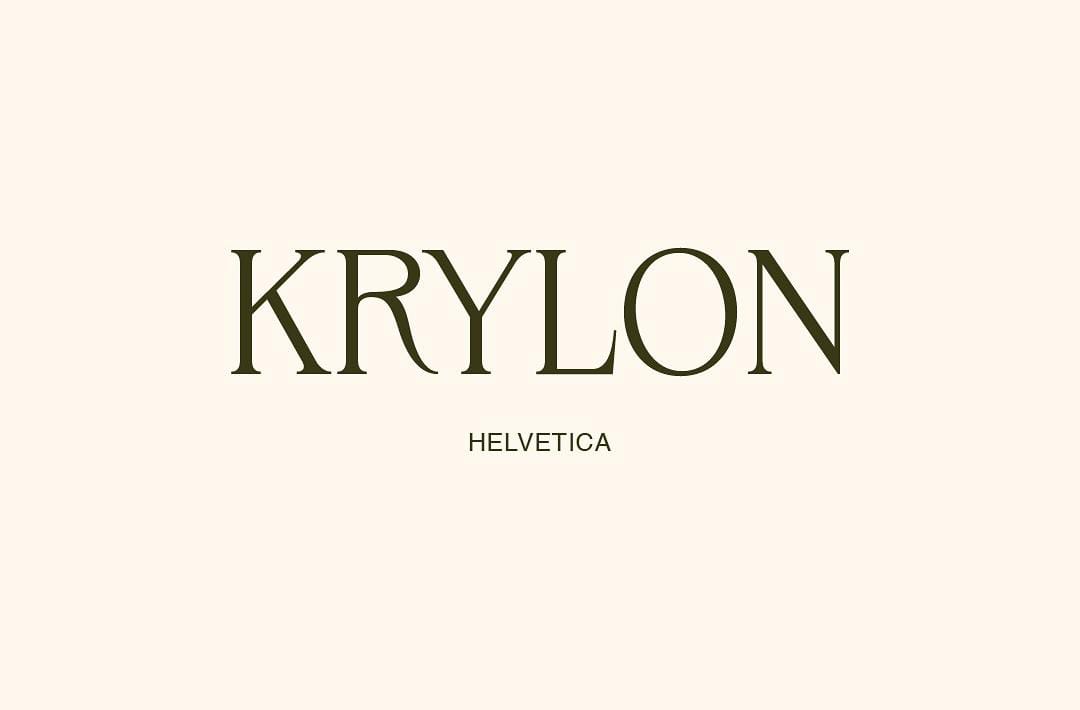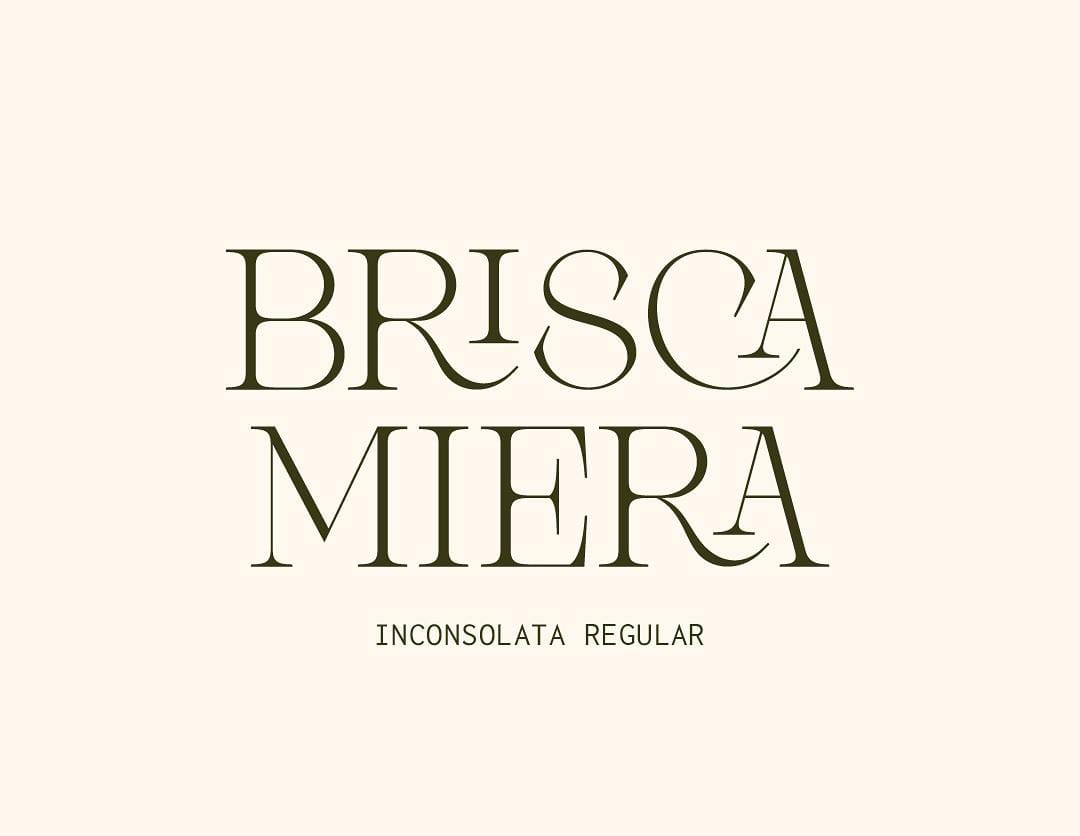
Untuk memastikan branding tampil profesional maka penting untuk memilih kombinasi elemen yang profesional. Tipografi menjadi salah satu elemen penting dalam branding sehingga harus dipilih yang relevan. Untuk kebutuhan brand kecantikan, kombinasi font harus tampil elegan, mewah dan minimalis agar relevan.
Brand kecantikan identik dengan citra yang feminim, elegan dan mewah, hal ini akan terlihat melalui penggunaan elemen-elemen yang elegan. Desain brand kecantikan yang elegan akan meningkatkan daya tarik visual dan menarik perhatian target pasar. Untuk pilihan gaya tipografi yang digunakan harus dipilih yang elegan, unik dan sesuai dengan citra brand.
STYLE LOGO KECANTIKAN
Brand kecantikan sendiri memiliki ciri khas utama desain logo yang bersih, sederhana dan elegan. Selain itu, menggunakan font yang elegan, tipis dan memiliki garis yang halus agar mudah dibaca dan mewah. Brand kecantikan sendiri memiliki banyak jenis bisnis seperti kosmetik, skincare, salon, spa dan nail art. Pada umumnya desain logo untuk brand kecantikan akan memiliki ciri khas seperti:
Bentuk Logo Sederhana
Untuk merepresentasikan brand kecantikan, ciptakan bentuk logo yang sederhana dan minimalis. Gunakan bentuk ikon sederhana sehingga menciptakan desain logo yang minimalis dan profesional.
Logo sederhana biasanya akan memiliki style garis tipis dan style ikon line art. Gunakan bentuk ikon sederhana seperti gambar bunga, siluet wajah dan ikon alam. Hindari menggunakan banyak elemen agar menciptakan desain yang sederhana.
Warna Netral dan Lembut
Untuk warna yang digunakan, desain kecantikan akan relevan menggunakan warna yang sederhana pula. Batasi jumlah warna, hanya gunakan satu warna solid atau dua warna saja. Jika menggunakan dua warna, kombinasi harus lembut tidak boleh mencolok.
Penggunaan warna netral seperti krem, putih, hitam dan abu-abu sering digunakan sebagai branding warna brand kecantikan. Selain itu gunakan juga warna pastel yang lebih untuk menciptakan visual logo yang elegan. Kedua warna netral dan warna pastel akan mendukung visual brand bang elegan.
Style Ikon Geometris dan Line Art
Biasanya logo kecantikan seringkali hanya menggunakan huruf inisial agar tampil sederhana dan profesional. Kombinasi font elegan akan menciptakan desain brand kecantikan yang mewah dan feminim. Bentuk ikon tidak boleh menggunakan font tebal dan bentuk yang kaku, tetapi harus halus dan elegan.
Brand kecantikan juga sering menggunakan font bergaya geometris dan font tipis sehingga tampil sederhana dan bersih. Jika desain brand menggunakan ikon gambar alam atau siluet biasanya menggunakan style line art. Style line art yang tipis akan relevan dengan kombinasi font elegan yang juga tipis.
Tipografi Bersih dan Kombinasi Elegan
Desain brand kecantikan juga memiliki ciri khas penggunaan font sederhana, bersih dan memiliki garis yang elegan. Font tidak akan memiliki bentuk geometris yang kaku tetapi geometris yang elegan. Seringkali penggunaan font tipis populer untuk menciptakan kesan brand feminim dan elegan.
Kombinasi font elegan yang cocok untuk brand kecantikan seperti serif dan sans serif yang elegan. Kombinasi font script tipis dan font serif elegan juga akan harmonis dan relevan dengan citra brand. Gaya tipografi elegan akan membantu menciptakan kesan elegan, mewah dan premium.
KOMBINASI FONT UNTUK BRAND KECANTIKAN
Untuk digunakan dalam desain brand kecantikan seperti kosmetik, skincare dan lainnya, gunakan font elegan. Jika ingin menggunakan kombinasi dua gaya font berbeda, pilih yang harmonis dan elegan. Berikut beberapa kombinasi font elegan untuk brand kecantikan yang kontras tetapi juga harmonis:
Vonder dan Raleway
Jenis font serif tersebut memiliki visual yang elegan, bersih dan sederhana sehingga cocok untuk mencerminkan brand kecantikan. Font serif tersebut tampil harmonis dengan kombinasi font sans serif sederhana seperti Raleway. Kedua font tampil kontras karena memiliki bentuk huruf yang berbeda dan style huruf yang berbeda.
Font serif tersebut memiliki gaya font yang tinggi dan ujung serif yang tajam. Kontras garis yang tebal dan tipis pada desain huruf tersebut menciptakan gaya elegan. Kombinasi font cocok untuk merepresentasikan brand kecantikan seperti kosmetik agar berkesan mewah.
Font Matter Sculpit dan Archivo Reguler
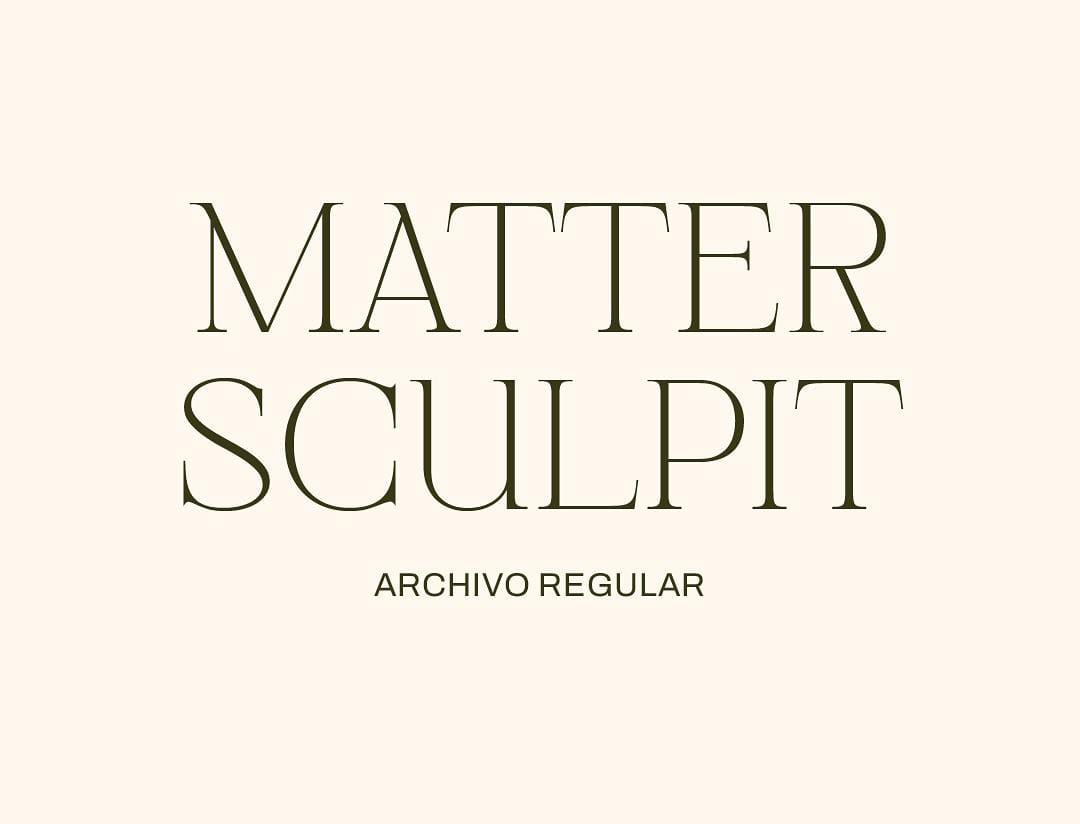
Gaya huruf serif seringkali digunakan untuk merepresentasikan brand kecantikan karena banyak yang memiliki style elegan. Terutama serif modern dengan garis halus, sudut tajam dan ujung serif lancip. Font serif tersebut memiliki style font yang tipis dan bersih sehingga bisa mencerminkan brand kecantikan yang elegan.
Kombinasi font serif dan sans serif tersebut tampil kontras karena memiliki style huruf yang berbeda. Brand kecantikan dengan kombinasi font elegan tersebut bisa menciptakan logo profesional dan berkesan mewah.
Desain logo bisa tampil lebih dipercaya oleh konsumen jika menggunakan font yang elegan. Font elegan bisa digunakan untuk menciptakan logo kecantikan yang mewah. Logo yang mewah akan meningkatkan kesan produk kecantikan yang premium dan bisnis yang dapat dipercaya.
Kombinasi gaya font elegan akan efektif untuk merepresentasikan brand kecantikan seperti kosmetik, skincare, MUA dan salon spa. Gaya huruf yang halus, tipis dan minimalis akan menciptakan tipografi logo yang mewah. Penting untuk memilih style font elegan yang sesuai dengan citra brand agar profesional.